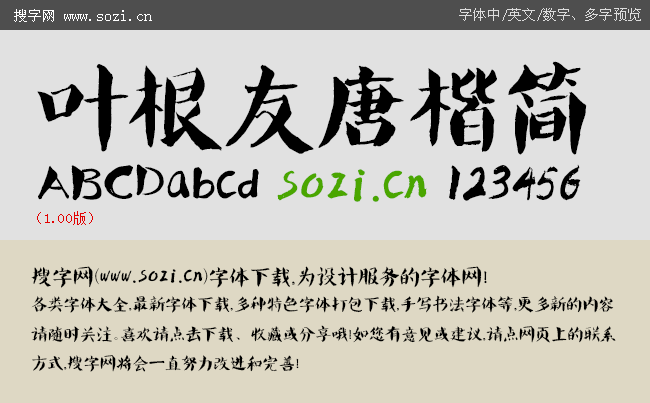
葉根友唐楷簡(jiǎn)
搜字網(wǎng)給大家提供一款葉根友唐楷簡(jiǎn)中文書法字體下載。葉根友唐楷簡(jiǎn)是特楷字體的姊妹風(fēng)格字體,在延續(xù)特楷字型基礎(chǔ)上重新創(chuàng)意,整個(gè)字型較之前的特楷更加嚴(yán)謹(jǐn),風(fēng)格遒勁,自然而不失灑脫,是一款標(biāo)題用字不錯(cuò)的選擇。葉根友唐楷簡(jiǎn)體可用于卡通設(shè)計(jì)、廣告設(shè)計(jì)、平面設(shè)計(jì)、印刷包裝、報(bào)紙雜志等廣告設(shè)計(jì)場(chǎng)合使用。